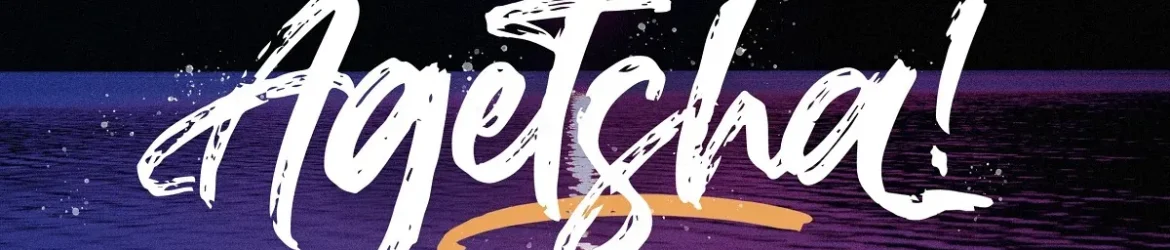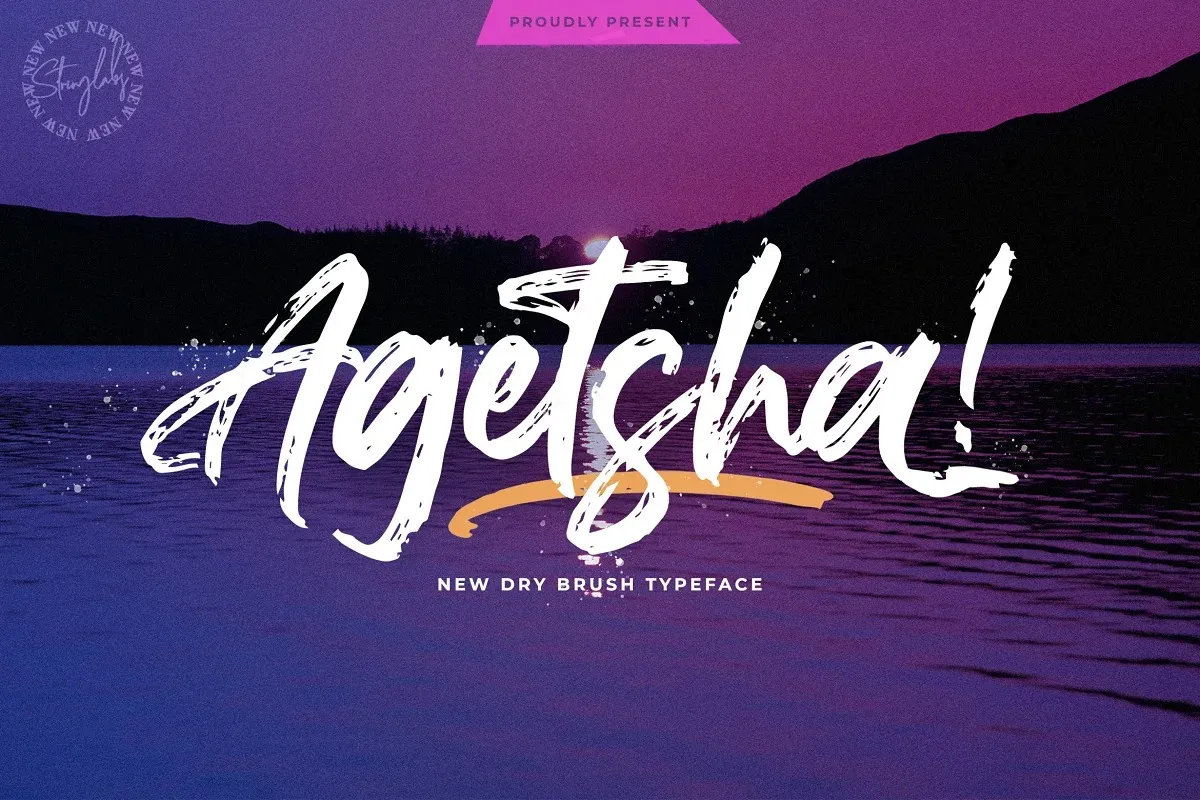
Agethsa Font – Fonte Grátis
Agethsa Font
A Agethsa Font é uma elegante escolha para designers que buscam adicionar uma toque delicado às suas criações digitais. Esta fonte brush moderna foi criada pelo StringLabs, oferecendo um conceito capturador e arrojado perfeito para projetos de marca, logotipos, design de casamentos, posts da mídia social, anúncios, embalagens de produtos, designs de produto, etiquetas, fotografias e até mesmo água-marinhas. Seja você um designer gráfico ou uma empresa que busca personalidade em suas propostas visuais, a Agethsa Font é perfeita para qualquer projeto que precise de toques manuscritos sofisticados. Sua simplicidade elegante torna-a adequada não apenas para trabalhos profissionais, mas também para aplicações pessoais e artísticas. Descubra por si mesmo como essa fonte brush pode transformar seus projetos em verdadeiros momentos de criação.